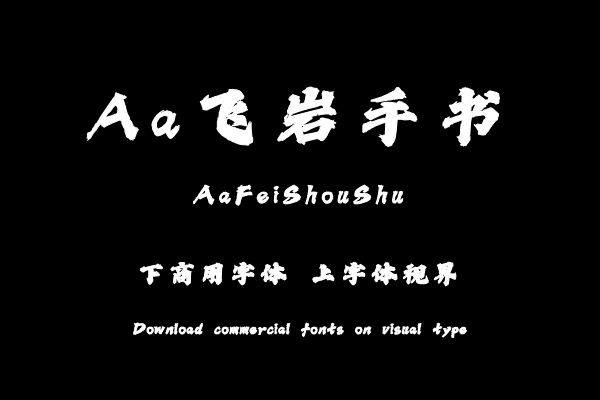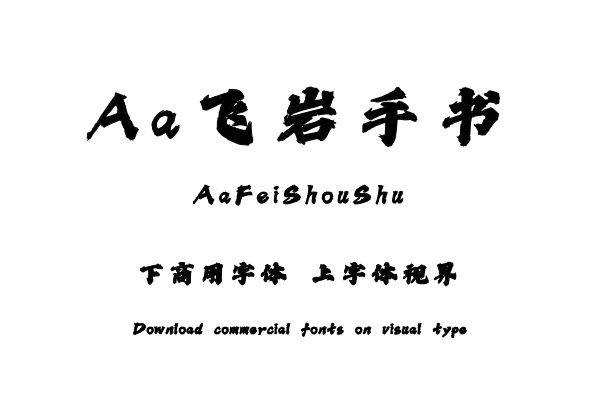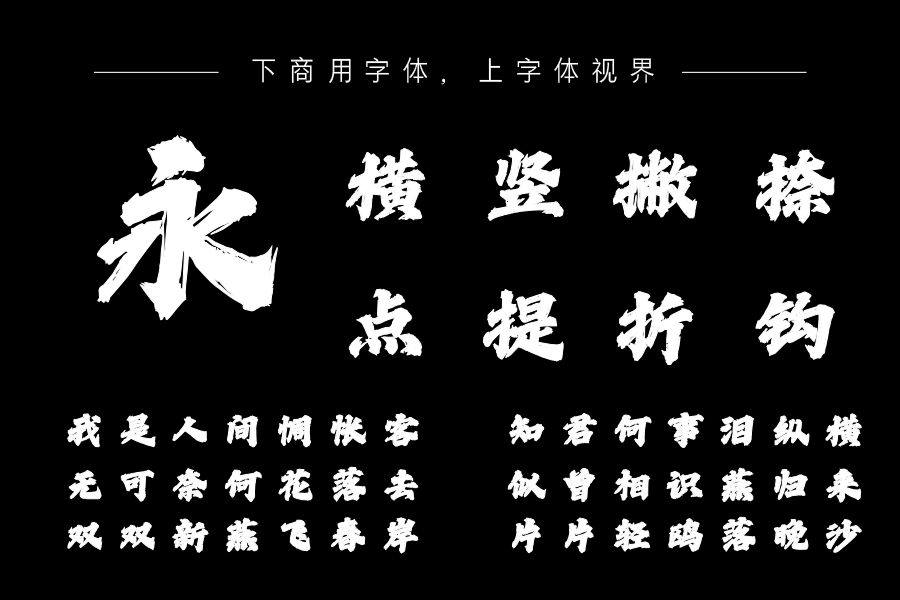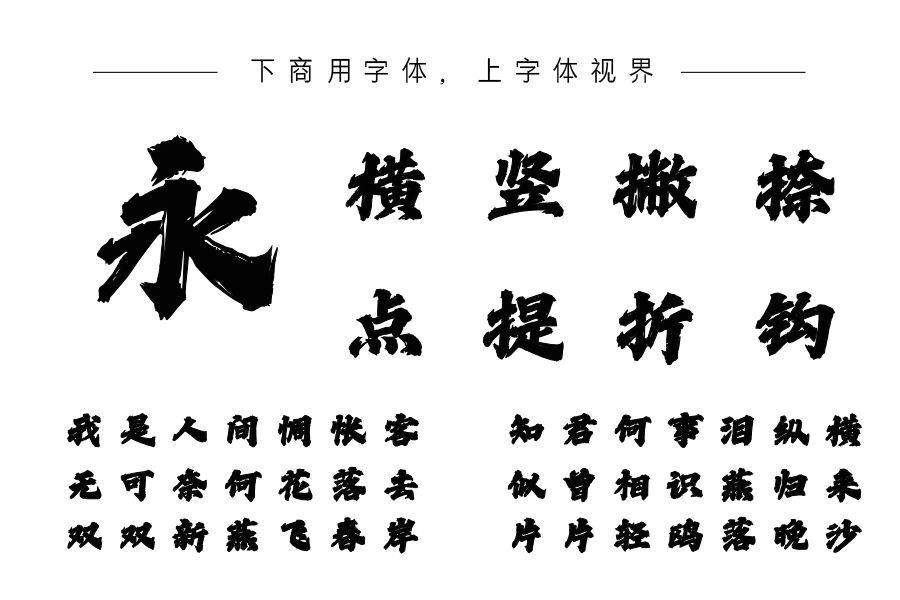
本字体整体取势于魏碑,笔画化曲为直,方头方脑,生猛可爱,内细外粗向往辐射,加上丰富的飞白,向外放射的势头更强,传达力量与速度感的同时有呆萌的趣味。购买须知:“下载服务费”与“字体VIP”所获得字体 仅用于个人非商用, 商用请联系付费授权。本字体为电脑用字,手机没有root权限不支持直接手机换字(手机如何root,请自行百度搜索教程)。购买前请先 了解清楚后再付款 ,字体为虚拟产品无法回收 一旦购买不支持退款。